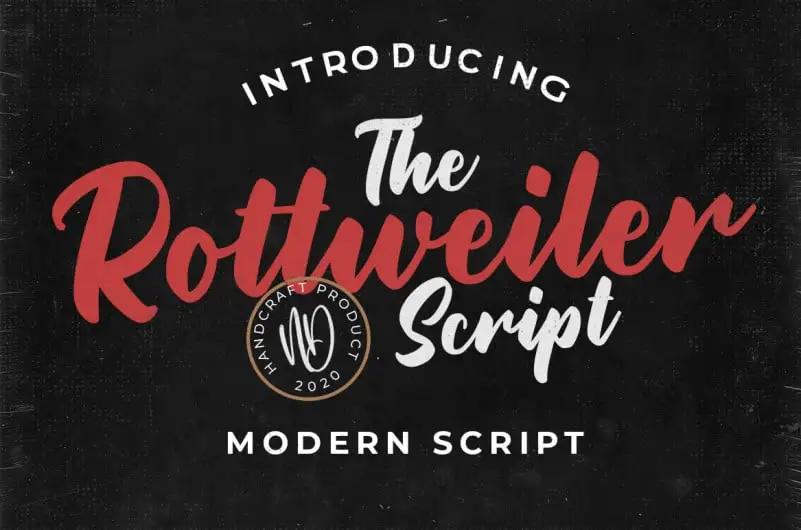
Rottweiler Script Font – Download Grátis
Rottweiler Script Font é uma fonte escrita a mão com um estilo clássico e retrô. Ideal para inúmeras aplicações criativas que incluem logos, cartazes, cartões de visita, embalagens de produtos, camisetas e etiquetas, Rottweiler oferece todas as letras maiúsculas e minúsculas, números e sinais de pontuação. A fonte também tem ligaduras e suporte para múltiplas línguas, o que a torna versátil e adaptável para um grande número de usos. Com seu estilo agradavelmente descontraído e personalizado, essa fonte é uma escolha ideal tanto para designers profissionais quanto para artistas independentes buscando adicionar um toque único e emocionante às suas criações gráficas.
Designer: nurfdesigns